Türkçe Karakter Destekli Font Nasıl Seçilir?
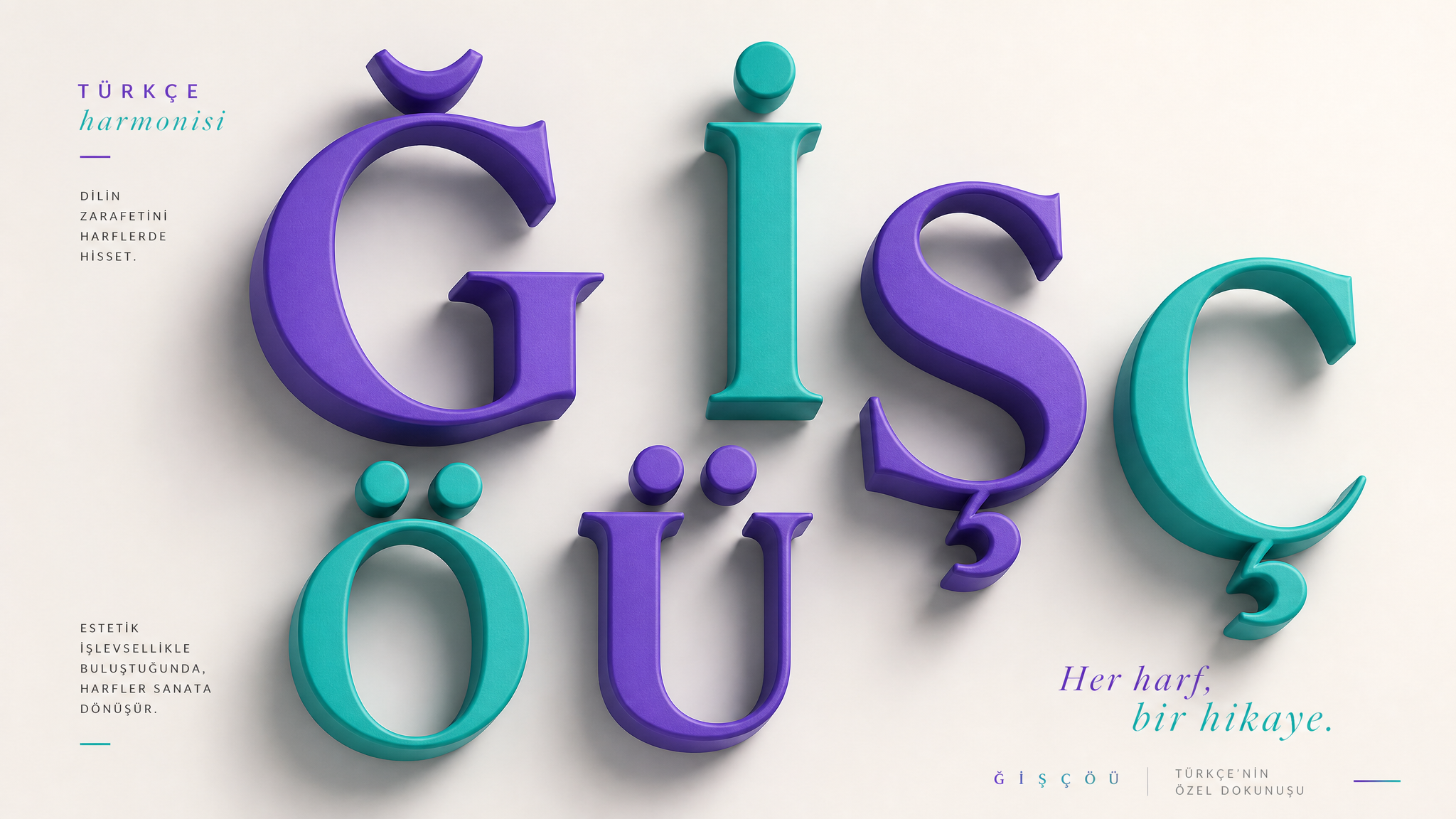
Bir fontun Latin alfabesini desteklemesi, Türkçeyi eksiksiz desteklediği anlamına gelmez. Tasarımın son aşamasında eksik Ğ, İ, Ş, Ç, Ö veya Ü karakteriyle karşılaşmak; başlığı bozabilir, marka tutarlılığını zedeleyebilir ve son dakika font değişikliğine yol açabilir. Doğru fontu seçerken görsel beğeni kadar karakter kapsamını da test etmek gerekir.
Test Edilmesi Gereken Karakterler
Font önizlemesinde şu diziyi kullanın: Çç Ğğ Iı İi Öö Şş Üü. Özellikle noktalı büyük İ ile noktasız küçük ı karakterlerini kontrol edin. Bazı fontlarda glif vardır ama tasarım diliyle uyumsuzdur; örneğin Ğ işareti harfe çok uzak veya Ş kuyruğu dengesiz olabilir.
Gerçek Metinle Deneyin
Sadece alfabe dizisine bakmak yeterli değildir. “İşbirliği”, “değişim”, “çözüm”, “özgürlük” ve “ışık” gibi Türkçe karakter içeren kelimeleri başlık ve paragraf boyutlarında deneyin. Harf aralığı, satır yüksekliği ve farklı ağırlıklarda karakterlerin dengesi bu aşamada görünür.
Font Ağırlıkları ve İtalik Stiller
Regular dosyada bulunan Türkçe glifler bazen Bold veya Italic dosyalarında eksik olabilir. Kullanmayı planladığınız her ağırlığı ayrı test edin. Değişken fontlarda weight, width ve italic eksenlerinde örnek metni dolaştırarak bozulma olup olmadığını kontrol edin.
Okunabilirlik ve Font Eşleştirme
Türkçe karakter desteği teknik bir zorunluluktur; okunabilirlik ise tasarım kararıdır. Uzun metinlerde açık harf boşluklarına ve güçlü noktalama işaretlerine sahip fontlar seçin. Başlık için karakterli bir display font kullanıyorsanız gövde metninde sade bir sans-serif ile denge kurun.
Kontrol Listesi
- Çç Ğğ Iı İi Öö Şş Üü glifleri mevcut mu?
- Tüm ağırlık ve italik dosyalarında destek sürüyor mu?
- Türkçe kelimelerde harf aralığı dengeli mi?
Sonuç
Türkçe destekli font seçimi yalnızca altı özel harfi bulmak değildir. Glif kalitesi, ağırlıklar arası tutarlılık, okunabilirlik ve lisans kapsamı birlikte değerlendirilmelidir. Kısa bir test listesiyle ilerlemek sonradan yapılacak pahalı değişiklikleri önler.